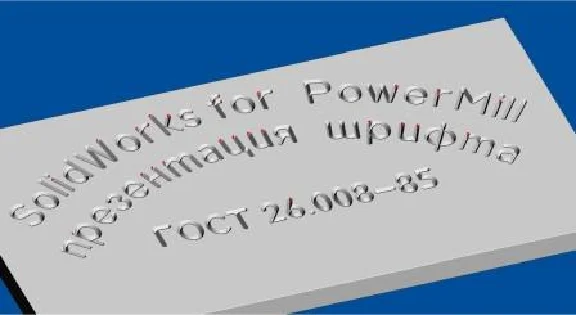
Шрифт разрабатывался под SolidWorks (возможно использование других CAD применяющих
системные шрифты) для последующего экспорта шаблона траектории в формате DXF в CAM
(например PowerMill)